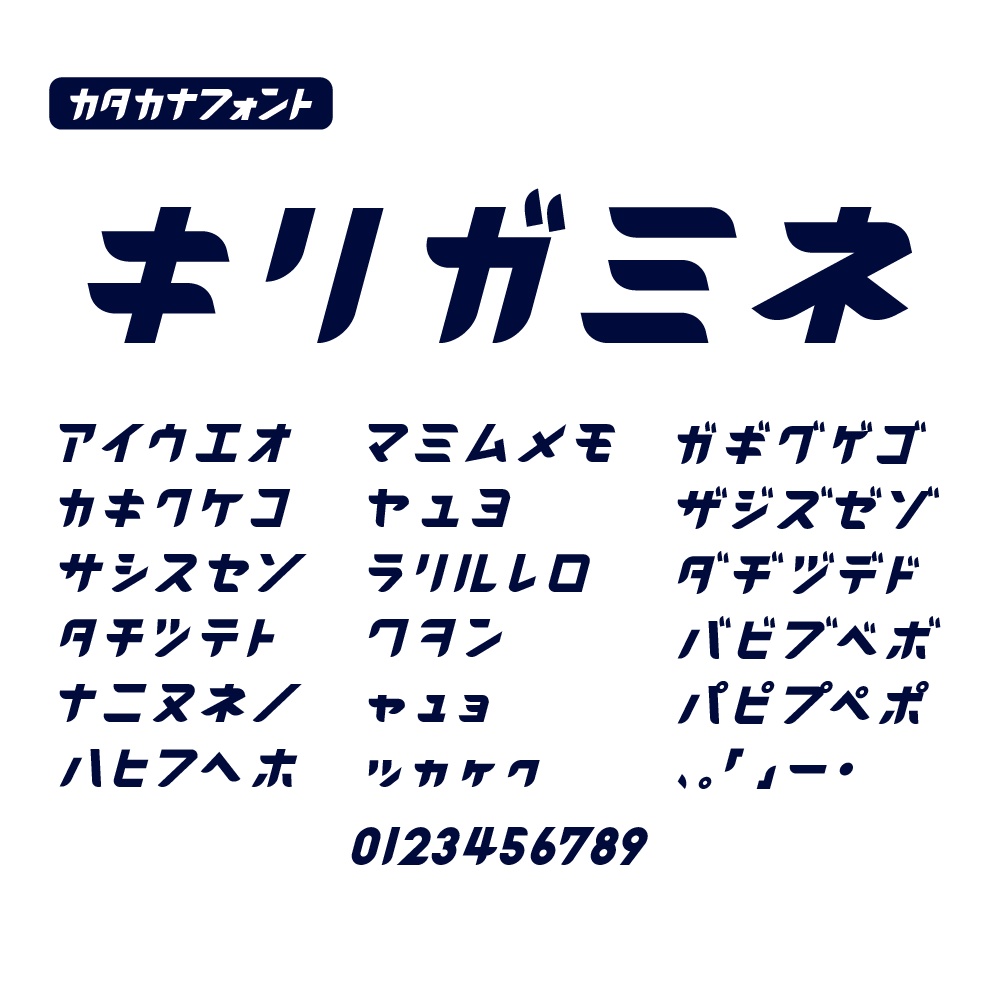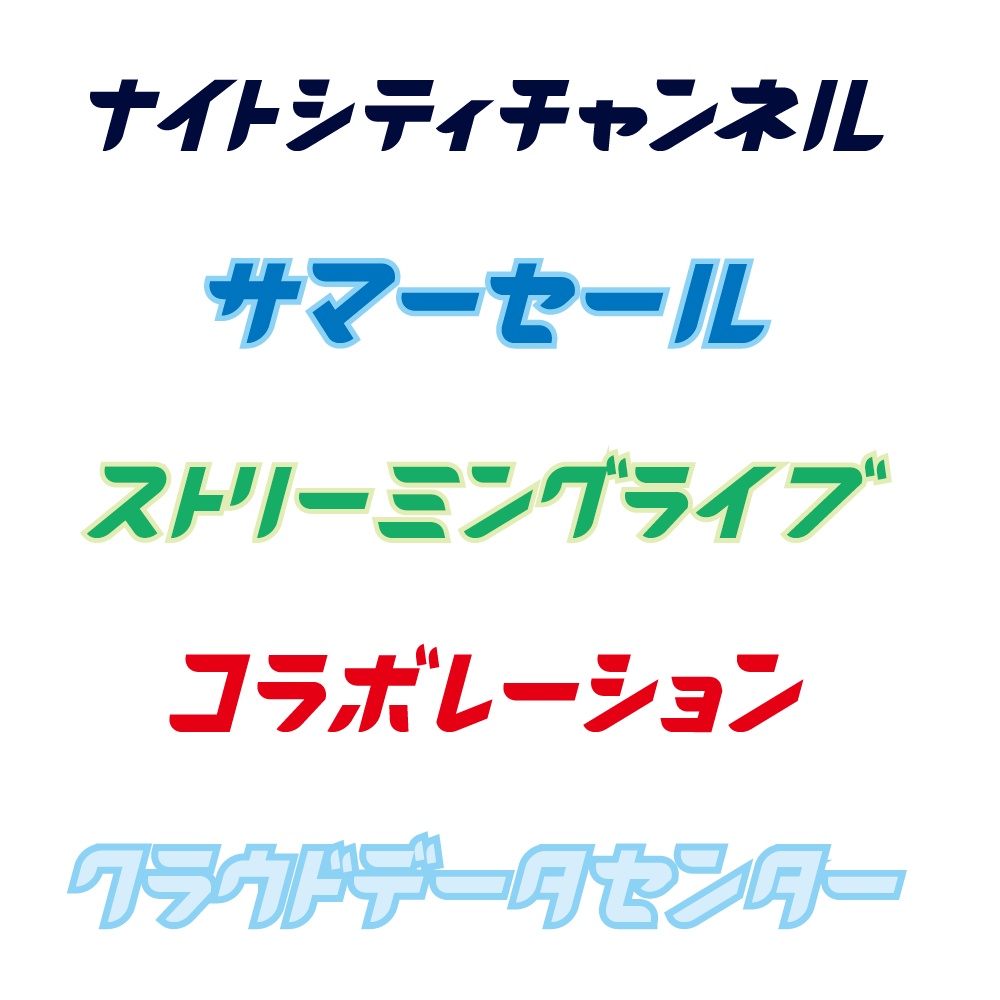
キリガミネ(カナ専用フォント)
【概要】 ソフトな曲線とインパクトを両立した、カタカナ中心の日本語フォントです。 ロゴ、見出し、配信サムネイルなど、インパクトのある場面で使いやすいようにデザインしました。 【収録文字】 ・全角カタカナ ・欧文数字 0〜9 ・一部記号(ー「」!?・ など、基本的な記号のみ) 【想定用途】 ・タイトルロゴ、ゲームロゴ ・動画サムネイル、配信レイアウト ・ポスター/フライヤーなどの見出し ・SNS 用画像 など 【対応環境】 ・フォント形式:OpenType フォント(.otf) ・動作確認済み:Windows 10 / Windows 11(日本語版) ・上記以外の OS(macOS など)や一部アプリケーションでもご利用いただける場合がありますが、作者は動作保証・サポートを行っておりません。 【カーニングについて】 ・カタカナ向けのカーニング情報を含んでいます。 ・Adobe Illustrator / InDesign などの DTP ソフトでは、文字パネルの「カーニング」を「メトリクス」に設定してお使いください。 ・Web フォントとして利用することも可能ですが、カーニングの反映状況はブラウザや環境に依存します。 環境によってはカーニングが反映されない場合があります。 【ライセンス/利用範囲(有料版)】 ・個人・商用利用どちらも可能です。 ・本フォントを使用して作成したロゴ、画像、動画、印刷物などの成果物は、自由に配布・販売していただけます。 ・ただし、本フォントを使用して作成したロゴ・マーク等を商標登録・意匠登録することはできません。 ・フォントファイル自体の再配布・再販売、フォントデータを改変して別フォントとして再配布する行為は禁止です。 ・1 ライセンスにつき、ユーザーが所有または管理する 2 台までの PC でご利用いただけます(同時使用は同一ユーザーに限ります)。 ・詳しい条件は同梱の「EULA.txt」を必ずご確認ください。 【ファイル内容】 ・Kirigamine.otf ・EULA.txt(利用規約) ・README.txt(概要と注意事項) 【注意事項】 ・本フォントおよび本フォントを用いて生成した画像・アウトラインデータを、機械学習・AI モデルの学習データとして使用することを禁止します。 ・フォントの表示結果やカーニングは、OS やアプリケーション、ブラウザ、描画エンジンの違いにより異なる場合があります。 必要に応じて文字間や行間を調整してご利用ください